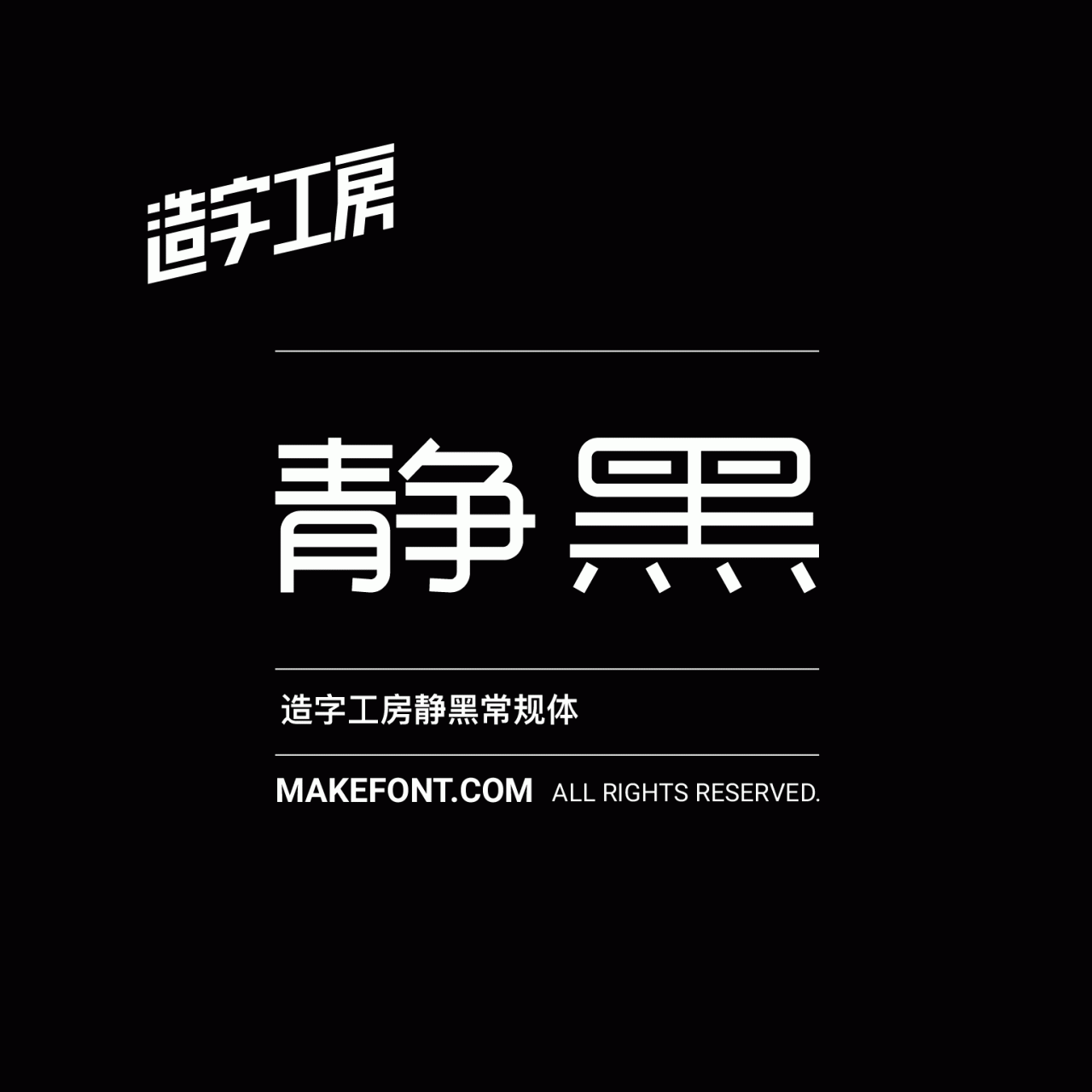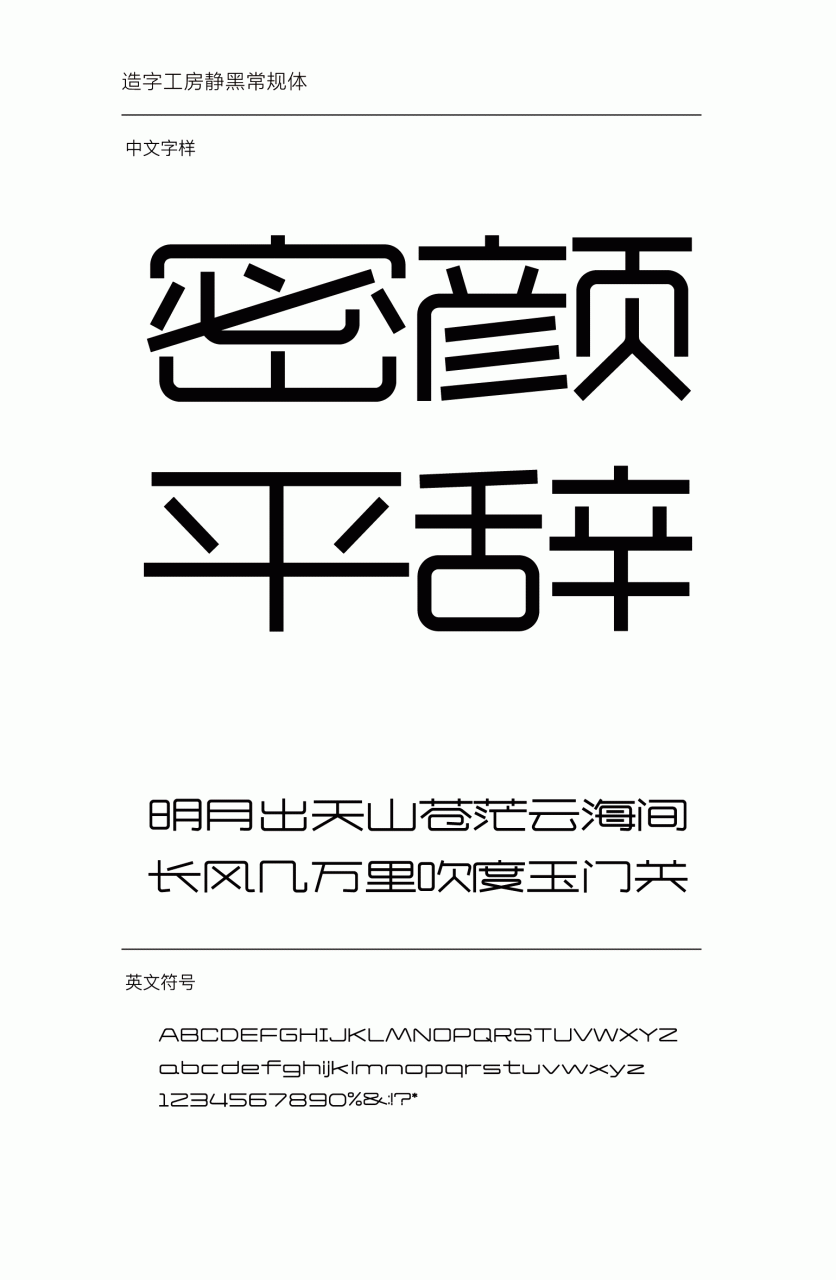
造字工房静黑常规体设计说明
造字工房静黑常规体,其字形扁平,此款字体在黑体字形基础之上巧妙创新,笔画纤细、简洁有力、字形简约、风格明显且易于阅读。结构清晰紧密而内敛,给人清新脱俗之感。适用于文字标题、广告设计乃至正文等视觉环境,有着极强的应用空间。 本字体为简体字库,采用OpenType/CID格式,Adobe-GB1-5编码。基于中华人民共和国GB2312-80字符集标准,另按需添加101个汉字。共收容字数6864CJK汉字,ASCII常用字符100个。